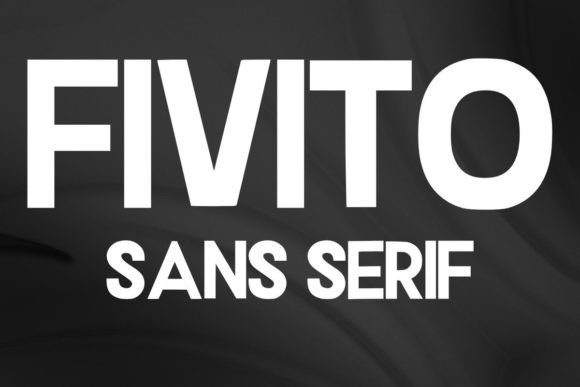
Fivito
Dicipta dengan ketepatan, Fivito menyediakan vektor yang bersih, tipografi yang licin dan lesen komersial untuk ketenangan fikiran.
Sama ada anda mencipta produk POD (Print on Demand), jemputan perkahwinan atau grafik media sosial, Fivito amat bersesuaian.